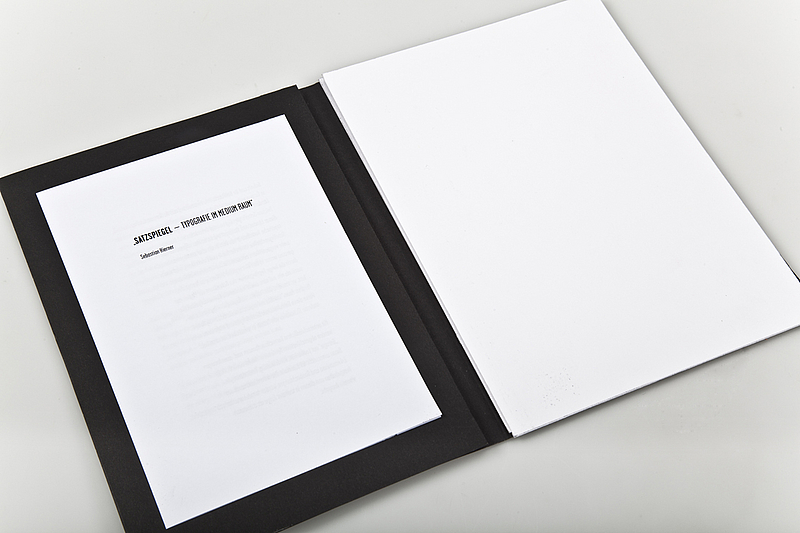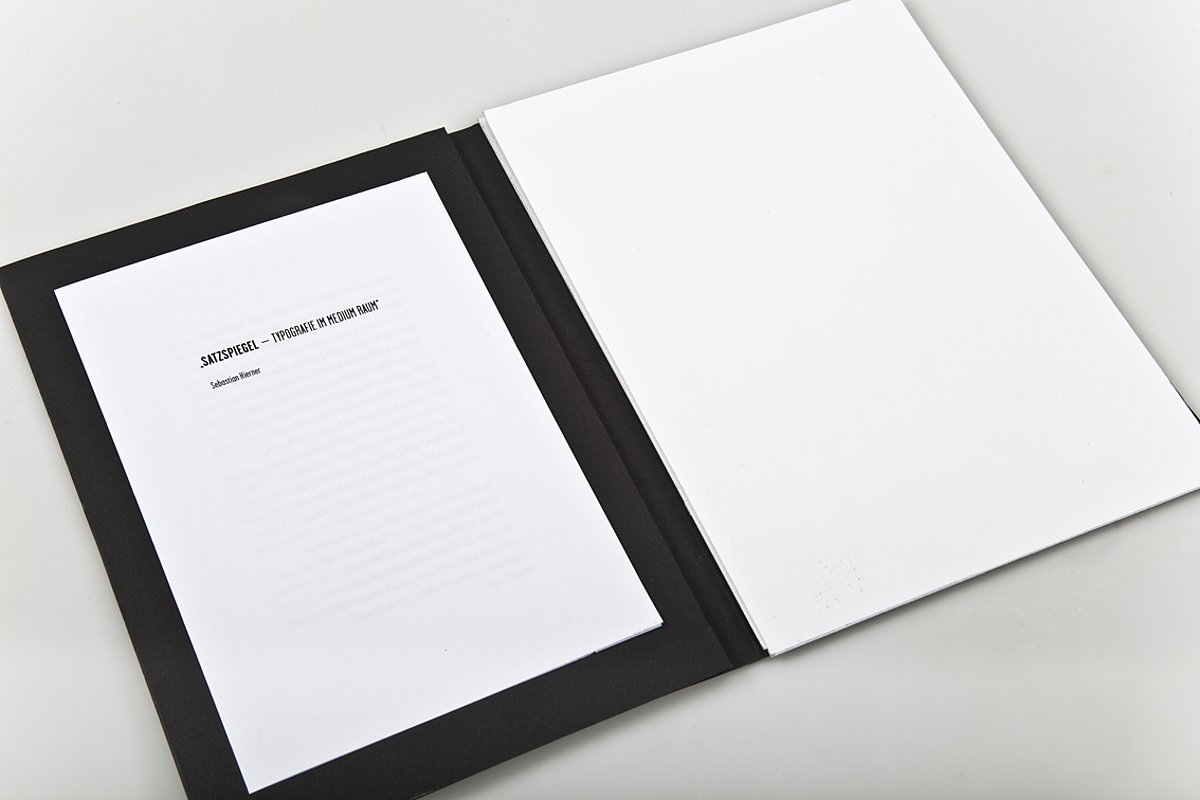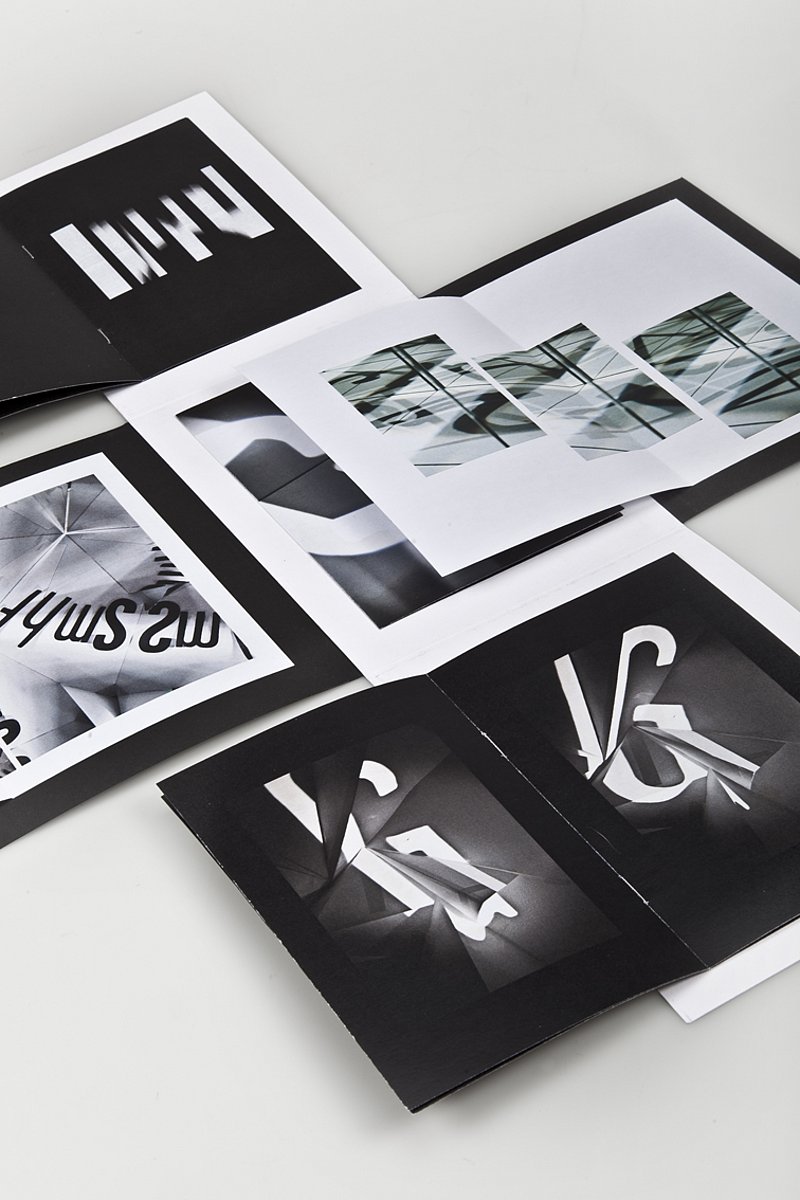
SATZSPIEGEL - TYPOGRAFIE IM MEDIUM RAUM
Sebastian Hierner
Fotografie, 2012
Grafik-Design und Fotografie
zusammen mit Bernhard Hierner / Kunstuniversität Linz - Industrial Design
Editorial Design, Foto-Dokumentation, Fotografie, 120 x 160 mm
Schrift und ihr Verbrauch, ihre Verwendung und ihr Konsum sind in Europa selbstverständlich geworden. Während in asiatischen Ländern Kalligrafie immer noch als Kunstform gilt und die Zeichenschrift, geprägt von der Geschichte und Tradition dieser Länder, zum Kulturgut wurde, ist das allgemeine europäische Verständnis von Schrift deren Herkunft und Entwicklung, werden immer mehr vergessen und europäische Schönschreib- Traditionen geraten weiter in den Hintergrund. Des Weiteren wird Typografie – durch die lange Gepflogenheit des Schreibens auf Papier – nur noch als ein, auf eine aufgebrachter Text verstanden. Das Projekt „Satzspiegel – Typografie im Medium Raum“ möchte auf experimentelle und analytische Weise diese Gewohnheiten hinterfragen und trägt so zu einer anderen Sichtweise von Schrift in westlichen Kulturen bei. Mit unterschiedlichen Versuchsaufbauten und -anordnungen werden abgeschlossene Systeme, in denen der Schrifttyp „Garage“ auf Lesbarkeit, Wiederholung, Veränderung im Raum untersucht wird, erstellt. Die daraus entstandenen Erkenntnisse und Beobachtungen werden fotodokumentarisch festgehalten und dienen in weiterer Folge als ästhetische visuelle Ausgabe. „Satzspiegel – Typografie im Medium Raum“ verwendet für die Versuche einerseits verschiedene Parameter wie Spiegel, Licht und den Raum, um das lateinische Alphabet zu analysieren und andererseits fotografische Mittel wie Kamera und Scanner um diese festzuhalten.